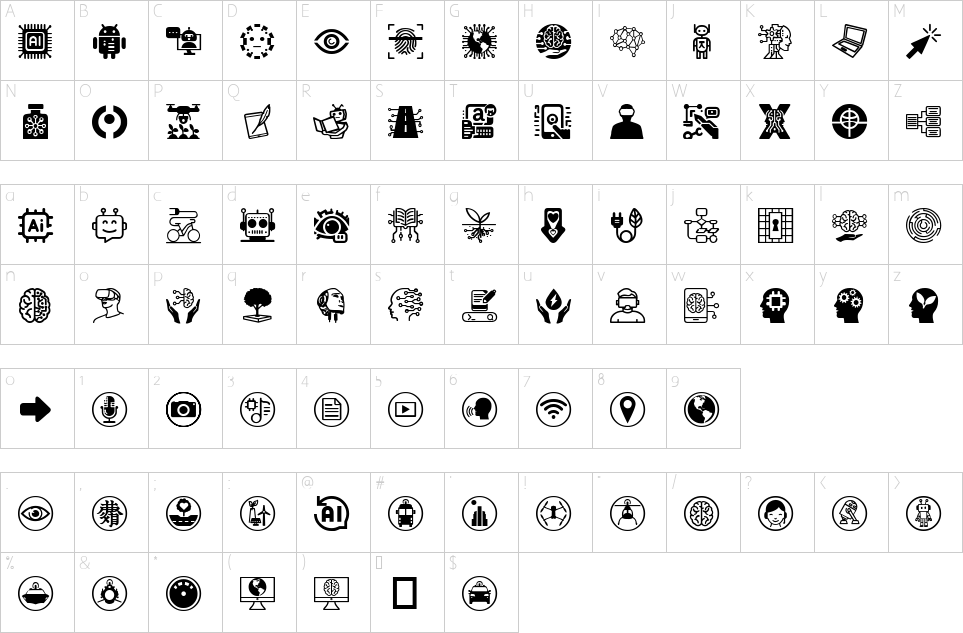
Descubra a nova fonte Artificial Intelligence, uma fonte criada especialmente para quem busca uma aparição moderna e funcional em seus projetos digitais. Desenvolvida pelo designer Glyphcraft, esta font é uma ótima escolha para quem busca um estilo minimalista e moderno. Com um design cuidadosamente pensado, a Artificial Intelligence oferece uma variedade de opções de tamanho e estilo, permitindo que você personalize suas criações de várias maneiras. As versões para Windows e Mac estão disponíveis para download, garantindo que você possa usar esta fonte em qualquer sistema operacional. Atualmente, a fonte já foi baixada 951 vezes, indicando a sua popularidade e qualidade. Se você está em busca de uma fonte de alta qualidade e com um design único, a Artificial Intelligence pode ser a solução que está procurando.